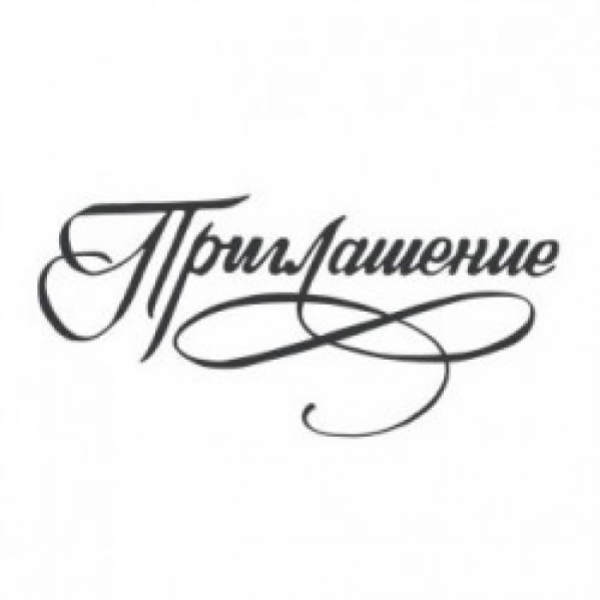
Приглашение на свадьбу своими руками. Мастер-класс с фото.
Мастер-класс по созданию приглашения на свадьбу своими руками не сложный, я расскажу о некоторых хитростях, а цветовую гамму можно выбрать абсолютно любую.
— Штамп «Приглашение»
Шаг 1.
Будем делать необычных бабочек из дырокола «сердце»
Складываем пополам бумагу для эскизов .
Намечаем для себя на дыроколе карандашиком отметку, от расположения этой отметки будет зависеть размеры бабочки. Можете поэкспериментировать.
Нажимаем и Оля- ля выходит замечательная бабочка! Нам нужно таких 10 штук!
Шаг 2.
Берем нашу салфеточку и по кругу приклеиваем бабочек на клей момент «Кристалл», должно получиться вот так:
Шаг 3.
Можно просто распечатать на принтере любым красивым шрифтом слово «приглашение» . Но отштампованное смотрится интереснее.
Я использовала акриловый блок, чтобы штамп было легко держать, но вы можете взять прозрачную коробку от дисков, стекло и так далее, силикон хорошо « липнет» к таким поверхностям.
Размер маленькой заготовочки : 3 см х 6,5 см . Штампуем!
Шаг 4.
Используем скотч и выстраиваем с другой стороны вот такую незамысловатую конструкцию.
В серединке вспененный скотч, по бокам тонкий двусторонний.
Приклеиваем!
Шаг 5.
Делаем Конверт – Обман из бумаги для эскизов.
Размер 9 х 14 см. Кармашек – на ваше усмотрение, у меня он вышел на 4см
Используем гелевую ручку для эффекта машинной строчки. Кармашек приклеиваем.
Шаг 6.
Делаем красивое местечко для самого приглашения.
Распечатываем на бумаге для эскизов эту парочку, аккуратно обводим контур гелевой ручкой и вырезаем!
Далее из этой же бумаги вырезаем прямоугольник размером 12 см х 8 см и в ход пускаем полубусинки, цветочки. По краям – опять же проходим гелевой ручкой.
Вот что у нас выйдет в итоге:
Шаг 7.
Собираем .
Приклеиваем все в нашу заготовку с помощью двустороннего скотча.
Не забываем про ленточку. (Можно обойтись и без нее)
Получаем вот такое приглашение)
А внутри пишем слова (здесь на ваше усмотрение, можете и напечатать)
Как сделать приглашения на свадьбу своими руками – пошаговый мастер-класс
Хотите удивить гостей еще до свадьбы? Сделайте приглашения на торжество своими руками по нашему мастер-классу.
Подготовка – первый шаг к красоте
- прозрачная леска;
- быстросохнущий клей;
- ножницы;
- бисерная игла;
- двусторонний скотч.
Мастер-класс по мастерству
А теперь следуйте пошаговому мастер-классу по созданию приглашения на свадьбу своими руками.
Отмерьте отрезок серебряной нити такой длины, чтобы хватило на два витка вокруг заготовки по ширине. С помощью бисерной иглы нанижите на нее в произвольном порядке бисер и бусины.
Проколов иглой небольшую дырочку на сгибе заготовки, протяните один конец нити внутрь открытки и аккуратно закрепите с помощью клея. Когда клей хорошо затвердеет, дважды обмотайте подготовленным отрезком верхнюю створку, действуя таким образом: натяните нить от исходной точки крепления по верхней створке так, чтобы все набранные бусины остались с лицевой стороны, далее протяните ее по внутренней стороне и с помощью иглы снова выведите на лицевую сторону, натяните еще одну линию и закрепите второй конец нити на сгибе заготовки с внутренней стороны.
В левой части открытки из цветов сформируйте букетик, выкладывая и приклеивая их на заготовку по одному.
Поверх проволочных стеблей букета наклейте небольшой бантик из атласной ленты.
17. Le More Collection Font Duo
18. Charlotte Script – Шрифт для приглашения на свадьбу
19. Shaping Heart – Lovely Serif 9000 7
Shaping Heart — элегантный и современные засечки с продуманными деталями, которые сделают вашу презентацию, логотип или свадебные приглашения более эффектными и красивыми!